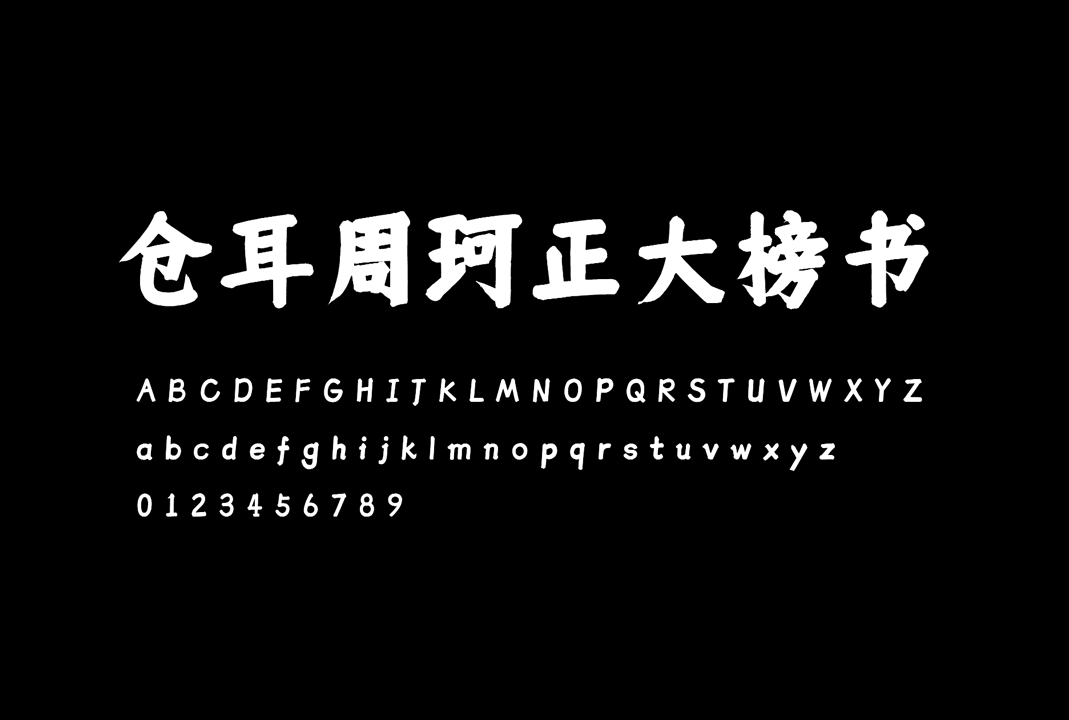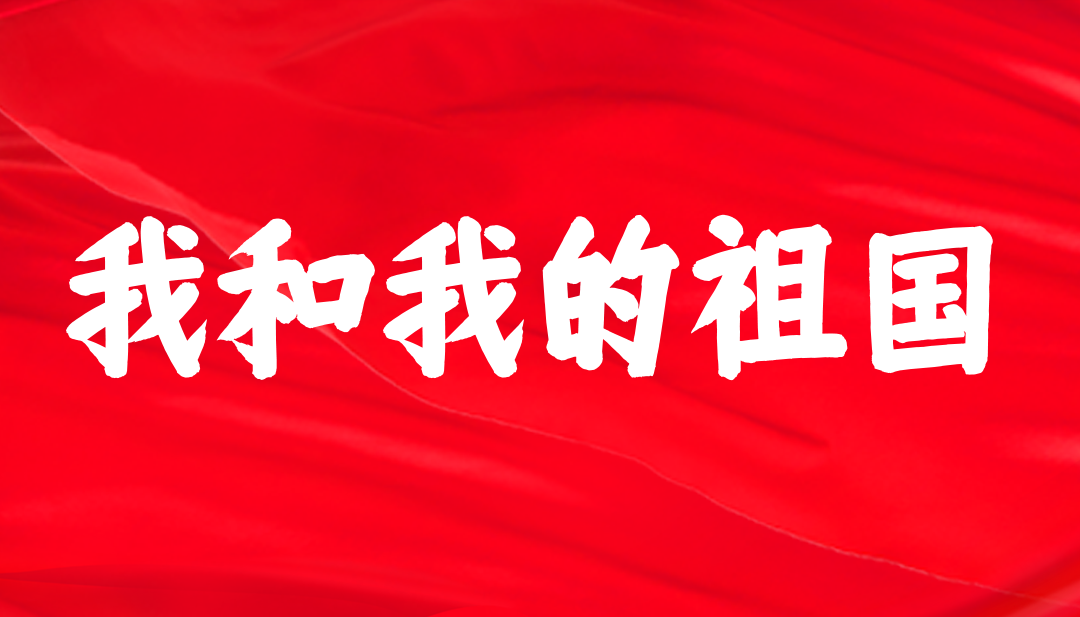
仓耳周珂正大榜书字体基于GB2312-80字符集汉字部分标准,共收容汉字6763个,英文及标点等常用字符245个。
仓耳周珂正大榜书字体是仓耳字库推出的一款适应于任何用户全领域永久免费商用的书法艺术字体。
该字体笔触粗细适中,字形端正,具有很好的视觉感,适合应用于艺术设计、平面宣传设计、网页设计,书法字帖等领域。